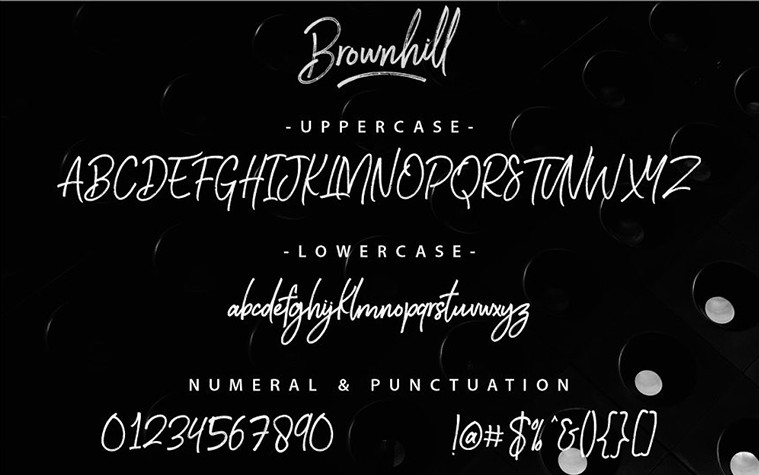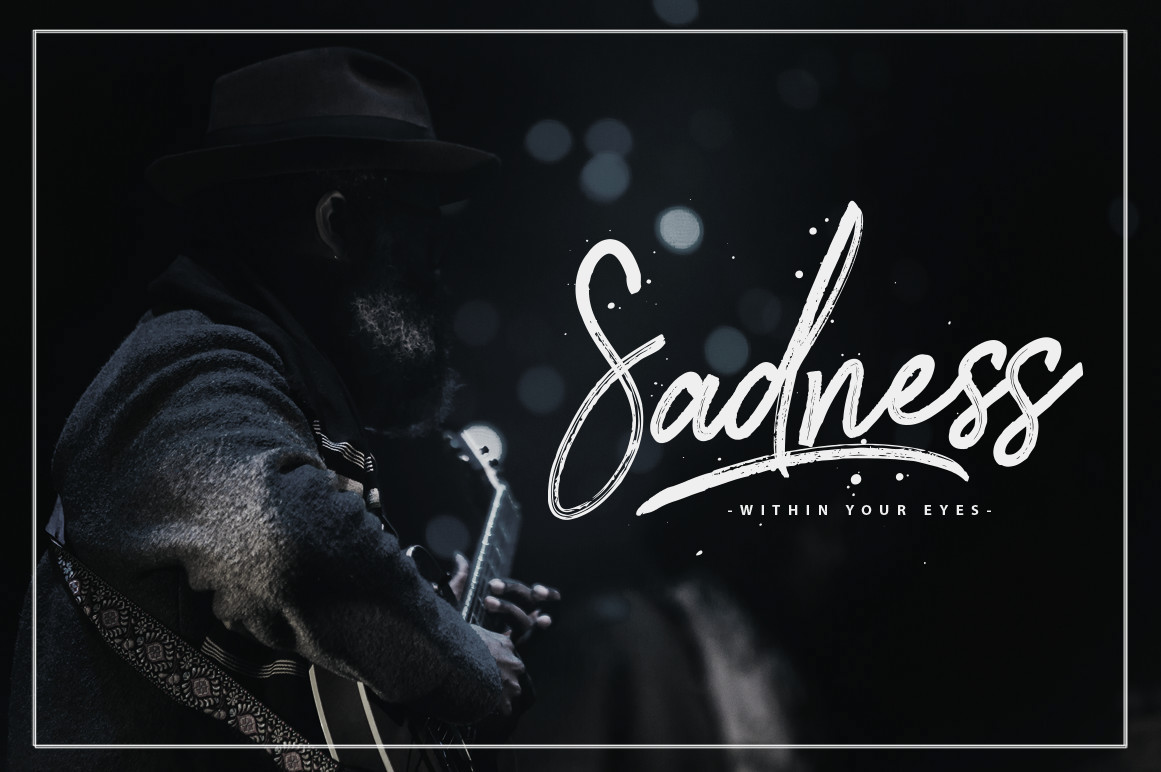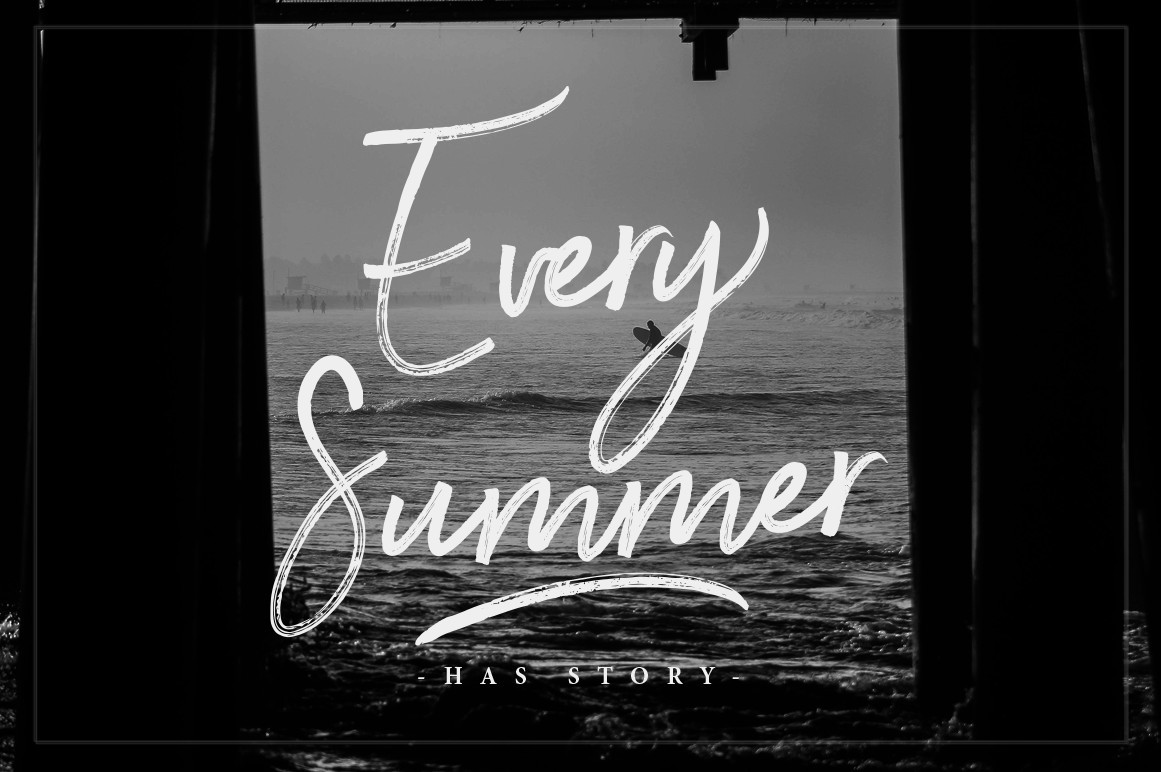
Để tạo nên dấu ấn riêng và sự mềm mại cho các bản thiết kế, việc lựa chọn một kiểu chữ viết tay tự nhiên đóng vai trò quan trọng. Font SVN Brownhill Script là bộ phông chữ mang phong cách thủ công với những đường nét uyển chuyển, gợi lên vẻ đẹp cổ điển nhưng vẫn đầy hơi thở hiện đại.
Đặc điểm thẩm mỹ đầy tinh tế của dòng font SVN Brownhill Script
Khác với các kiểu chữ hệ thống khô cứng, SVN Brownhill Script sở hữu nhịp điệu tự do với độ đậm nhạt biến thiên tinh tế, tạo nên chiều sâu thị giác cho văn bản. Phiên bản font Việt hóa SVN Brownhill Script đã được xử lý bảng mã Unicode chuẩn xác, giúp các dấu hỏi, ngã, nặng được đặt ở vị trí cân đối, duy trì vẻ đẹp thanh thoát xuyên suốt toàn bộ nội dung trình bày.
Sự ổn định của bộ phông này còn thể hiện ở khả năng truyền tải cảm xúc và định hình phong cách cá nhân cho thương hiệu. Những đường uốn lượn được tinh chỉnh kỹ lưỡng giúp văn bản toát lên vẻ sang trọng, phù hợp để làm điểm nhấn trên các bề mặt vật liệu tự nhiên như gỗ hoặc mica. Đây là lựa chọn phù hợp cho những dự án yêu cầu tính thẩm mỹ cao, đề cao sự tận tâm và gu thẩm mỹ sắc sảo của người kiến tạo trong từng sản phẩm đồ họa và kiến trúc chuyên nghiệp.
| Mục đích phù hợp | Logo homestay, thiệp mời, tiêu đề phối cảnh, decor |
Tư vấn trình bày: SVN Brownhill Script có cá tính mạnh và nét chữ mang tính trang trí cao. Để bản thiết kế đạt được hiệu quả thị giác hài hòa, bạn nên sử dụng phông chữ này cho các tiêu đề chính hoặc slogan và phối hợp cùng một phông Sans-serif tối giản cho phần nội dung thuyết minh chi tiết.
03 Ứng dụng phông chữ SVN Brownhill Script vào thực tế
Nhờ diện mạo giàu tính nghệ thuật và cá tính riêng, bộ phông chữ này mang lại giá trị thực tế cao trong khâu quảng bá và hoàn thiện các công trình kiến trúc hiện đại:
- Hệ thống nhận diện cho homestay: Những nét chữ mềm mại của SVN Brownhill Script rất ăn ý khi xuất hiện trên biển hiệu bằng gỗ khắc laser hoặc mica gương tại các khu nhà lắp ghép nghỉ dưỡng. Phông chữ này giúp không gian toát lên vẻ thư thái và đẳng cấp riêng.
- Thiết kế bìa hồ sơ năng lực dự án: Sử dụng font viết tay cho tiêu đề các trang lời tựa hoặc lời nhắn gửi giúp thể hiện sự tận tâm và phong cách làm việc chuyên nghiệp, gần gũi của đơn vị thiết kế đối với khách hàng và chủ đầu tư.
- Trang trí không gian nội thất nghệ thuật: Bạn có thể dùng font này để làm tranh quotes trang trí hoặc cắt chữ nổi đèn neon tại sảnh đón khách văn phòng container nhằm tạo điểm nhấn lôi cuốn và khơi gợi cảm hứng sáng tạo cho không gian làm việc.
03 Lưu ý để bố cục phông chữ SVN Brownhill Script đạt hiệu quả cao
Để khai thác vẻ đẹp của dòng font đặc thù này mà không làm rối mắt người xem, người thiết kế nên lưu tâm một số kinh nghiệm kỹ thuật sau:
- Hạn chế viết hoa toàn bộ ký tự: Đặc trưng của dòng phông Script là sự liên kết nhịp nhàng giữa các chữ cái viết thường. Việc viết hoa toàn bộ cụm từ sẽ làm mất đi nhịp điệu tự nhiên và khiến tiêu đề trở nên thô cứng, thiếu thẩm mỹ.
- Kiểm soát khoảng cách dòng: Do cấu trúc chữ thường có các nét móc vươn dài, bạn nên thiết lập khoảng cách dòng thoáng một chút để các ký tự không bị chồng lấn, giữ được sự minh bạch cho văn bản khi nhìn từ xa.
- Lựa chọn kích thước hiển thị phù hợp: Tránh sử dụng phông chữ này ở kích thước quá nhỏ trên các bảng thông số kỹ thuật, vì các nét mảnh mô phỏng viết tay có thể gây khó đọc nếu mật độ ký tự quá dày đặc.